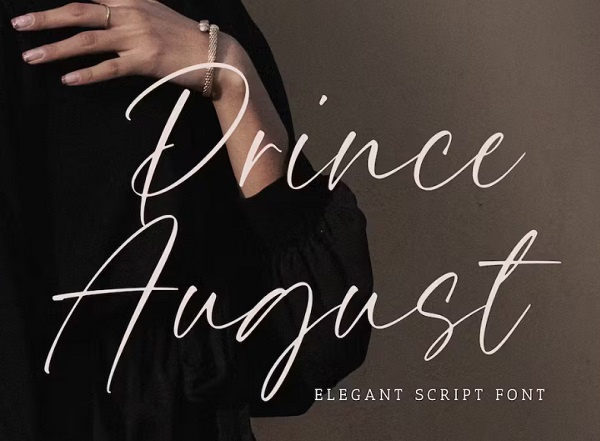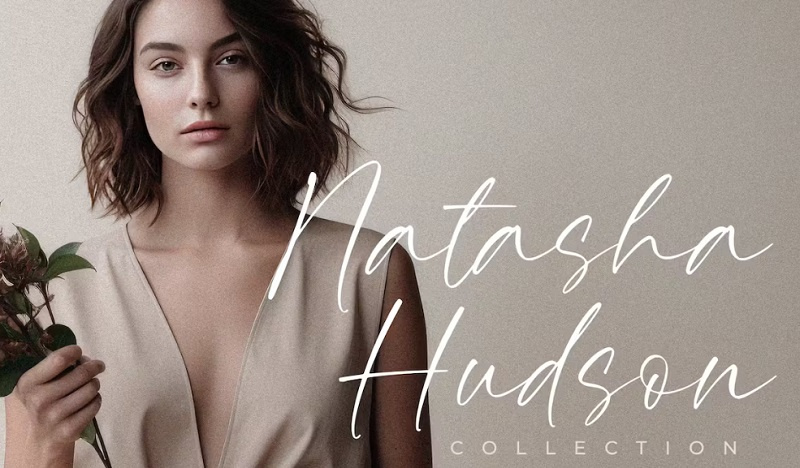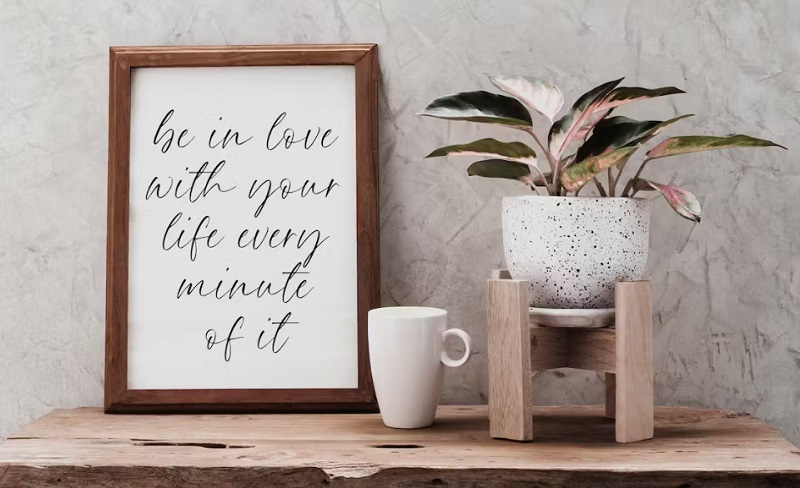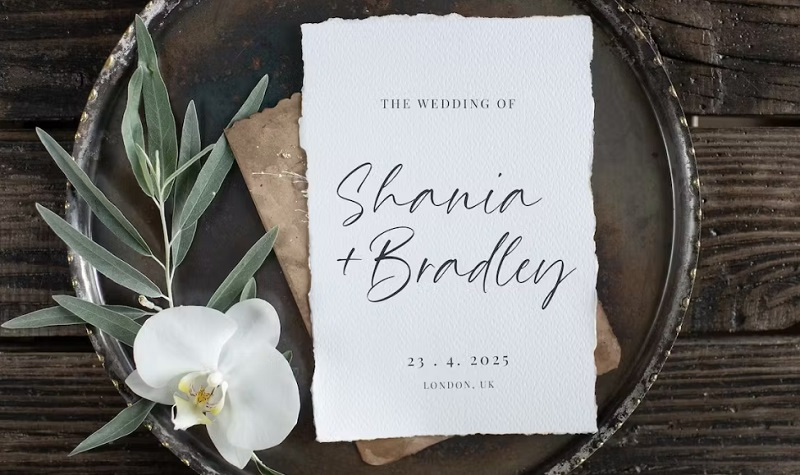
دانلود فونت انگلیسی Prince August
دانلود فونت انگلیسی Prince August یک فونت دست نویس زیبا، که به طور ویژه برای شما کاربران عزیز در سایت قرار داده شده است. این فونت برای بسته بندی محصول، پروژه برندسازی، مجله، رسانه های اجتماعی، عروسی یا در پس زمینه استفاده می شود. در ادامه با دانلود و مشاهده پیش نمایش این فونت انگلیسی زیبا با ما همراه باشید.
فونت انگلیسی Prince August
دانلود فونت Prince August
فونت زیبای انگلیسی Prince August
دانلود فونت انگلیسی دست نویس زیبا Prince August
✅ نام فونت انگلیسی: Prince August